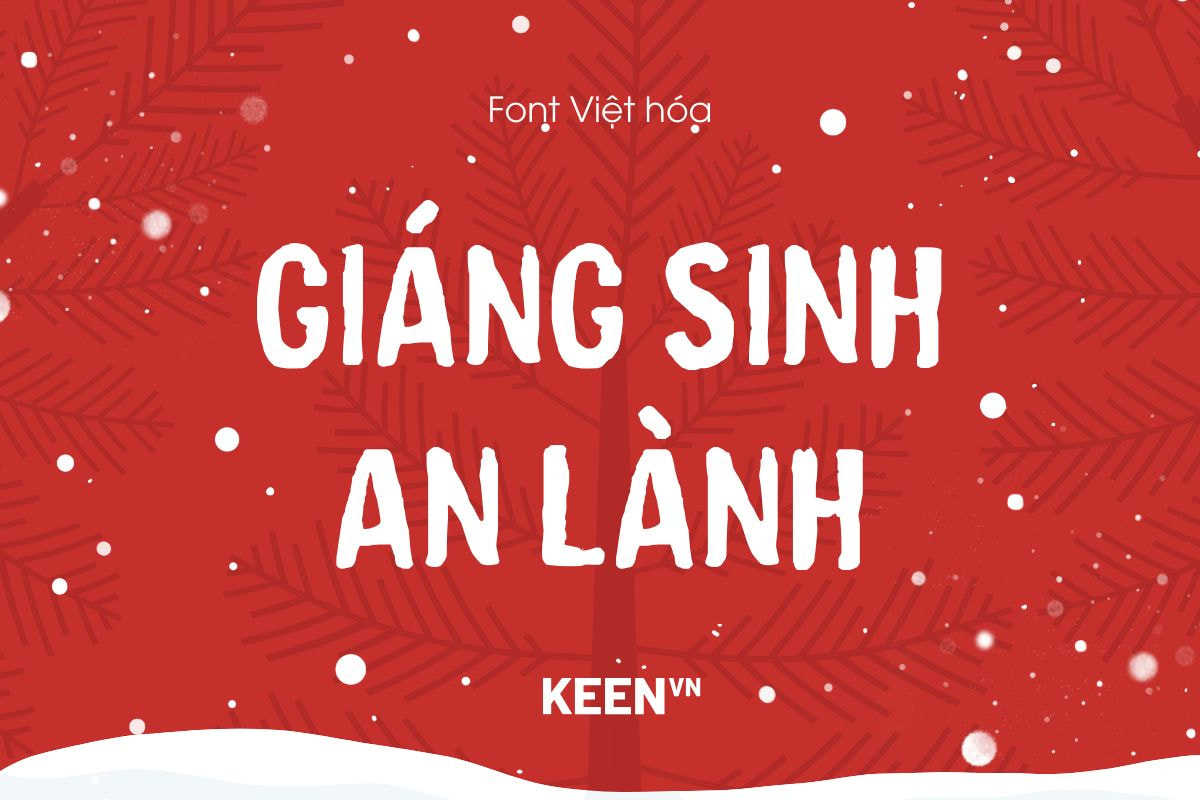
Font Việt hóa iCiel Dreams Unwound Regular
- Hỗ trợ đầy đủ dấu tiếng Việt
Font Việt hóa iCiel Dreams Unwound Regular mang đến một trải nghiệm thị giác đầy cảm xúc, nơi từng con chữ như được thổi hồn bằng những nét cọ loang mực tinh tế. Đây là một phông chữ SVG sans serif hoàn toàn viết hoa, mô phỏng chân thực chất liệu màu nước – điều mà các font vector truyền thống không thể làm được. Nhờ ứng dụng công nghệ SVG tiên tiến, từng ký tự giữ nguyên độ trong suốt, độ nhòe và kết cấu của nét bút lông ướt, tạo ra một cảm giác sống động và thủ công như đang được vẽ trực tiếp lên giấy.
Dreams Unwound Regular được thiết kế để gợi lên cảm xúc mơ màng, lãng mạn và có chút ma mị nhẹ nhàng. Các ký tự in hoa đậm nét, hơi tròn trịa và không đồng đều giúp font mang lại sự thân thiện và cá tính, khiến mỗi thiết kế trở thành một câu chuyện nhỏ đầy cảm hứng. Việc Việt hóa trọn bộ giúp người dùng thoải mái ứng dụng font trong nhiều dự án sáng tạo dành cho thị trường Việt Nam, từ ấn phẩm in ấn, bao bì, poster nghệ thuật đến những trích dẫn đầy cảm xúc trên mạng xã hội.
Với khả năng truyền tải cảm giác mềm mại, thủ công nhưng vẫn hiện đại, Dreams Unwound Regular là sự lựa chọn lý tưởng cho các tiêu đề cần điểm nhấn đặc biệt. Font trở nên hoàn hảo cho thiết kế logo mang màu sắc nghệ thuật, thiệp mời trang nhã, merch độc đáo, hay bất kỳ dự án nào đòi hỏi sự tinh tế và độc đáo. Nếu bạn muốn biến những dòng chữ thành những nét vẽ có hồn, đưa cảm xúc vào từng thiết kế, thì Dreams Unwound chính là chất liệu sáng tạo bạn không thể bỏ qua.